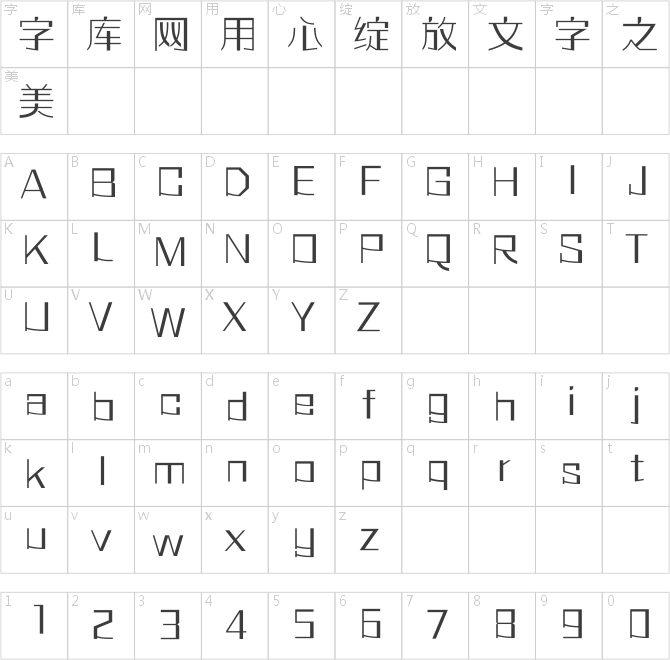
方正玩伴體 簡 Light 詳情頁
字體名稱: 方正玩伴體 簡
方正玩伴體 簡 Light
方正玩伴體 簡 Light字體字庫是一款讓人賞心悅目、百看不厭的中文字體,適合各類廣告和產(chǎn)品包裝設(shè)計應(yīng)用,字體大小2.13MB,格式為ttf字體,上傳用戶是韓國露韓,作者/版權(quán)方為方正字庫